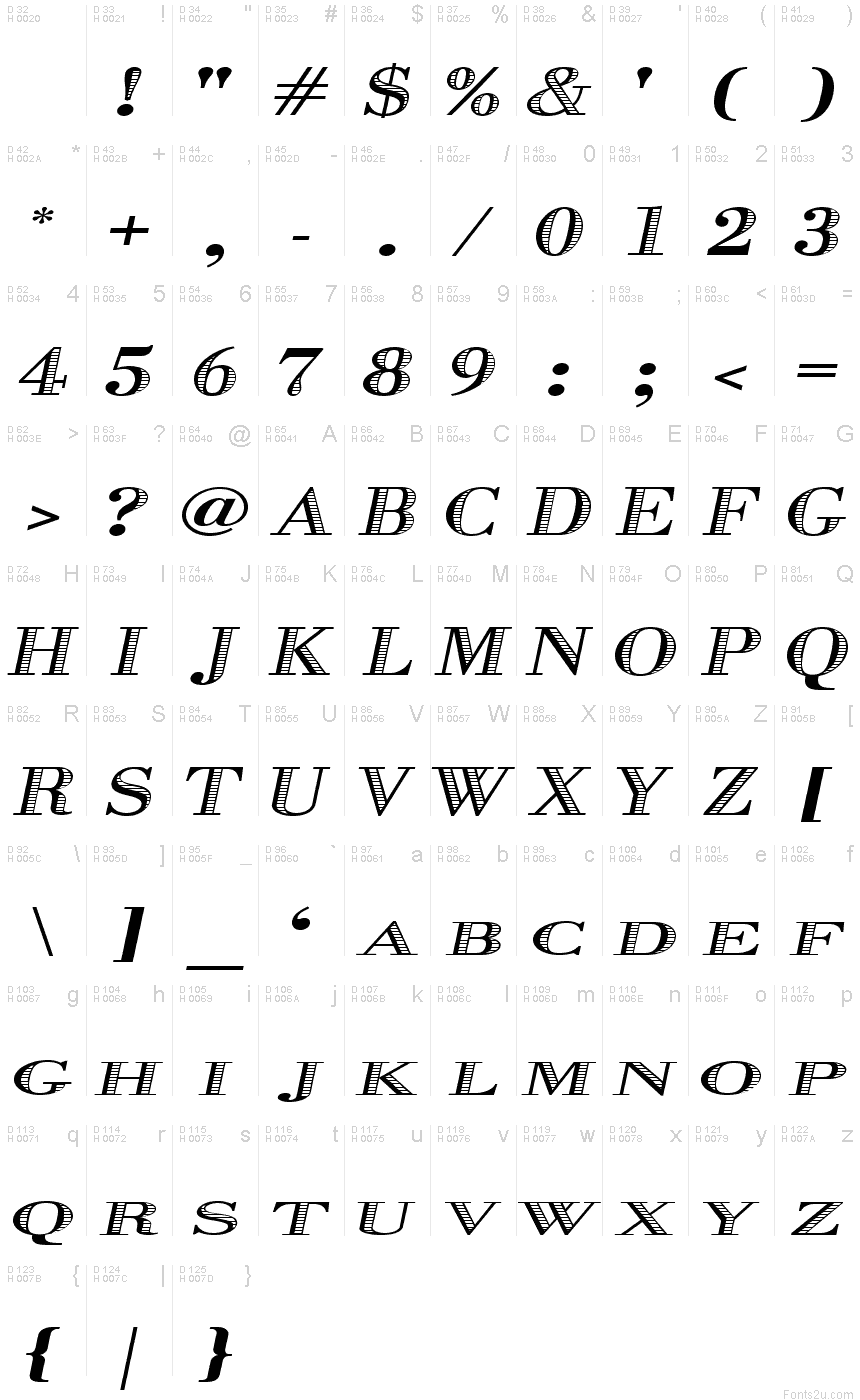
Graphis Oblique to darmowy krój displayowy w stylu retro. Każda litera jest pochylona i wypełniona gęstymi poziomymi paskami, które przywodzą na myśl stare taśmy filmowe lub świetlne szyldy wesołych miasteczek. Cienkie czarne obrysy i przewiewne linie wewnętrzne nadają znakom wyrazisty, grawerowany wygląd, który natychmiast budzi skojarzenia z estetyką vintage, nie tracąc przy tym nowoczesnej świeżości.
Dzięki Graphis Oblique Twoje nagłówki przyciągną uwagę na plakatach filmowych, ulotkach retro, szyldach teatralnych, logotypach vintage, projektach biletów czy śmiałych grafikach do mediów społecznościowych. Ten darmowy font najlepiej prezentuje się w dużym rozmiarze, gdzie kreskowana tekstura może w pełni wybrzmieć i przykuć wzrok. Połącz go z prostym bezszeryfowym krojem w tekście głównym, aby Graphis Oblique nadał całości charakteru, podczas gdy reszta treści pozostanie czytelna i przejrzysta.